其实字体应用在设计里很玄妙,因为没有不好看的字体只有适不适合的字体。在设计的时候适当的用上一些文字的辅助展示事半功倍,可以装饰画面起到画龙点睛的效果。今天要给大家分享几款用作ps设计里实用性比较高的字体,一下来看下面图片字体吧~
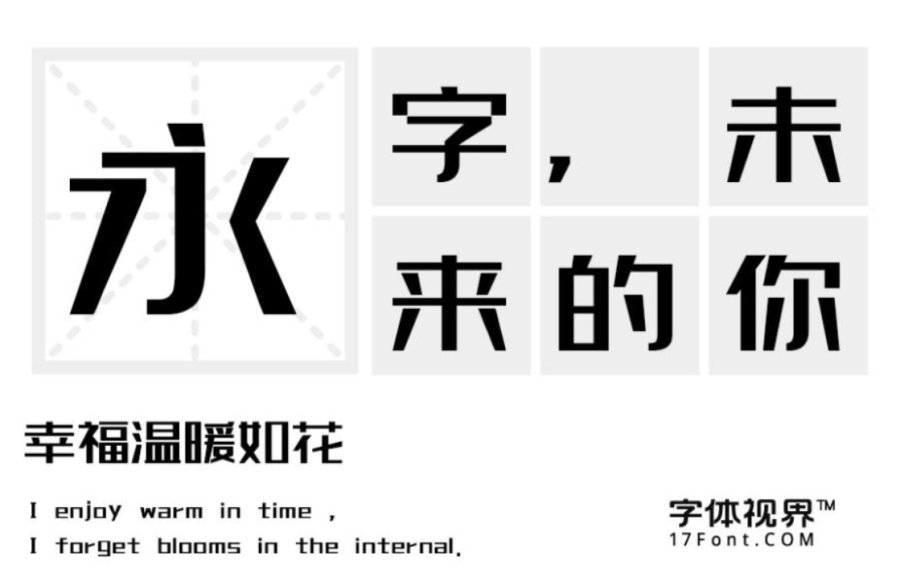
上首京东体:这款字体方中带圆,上细下粗,转折圆滑。整体特征圆柔、轻巧,时尚,适用于搭配标志、广告标语、商业广告等高端属性。
丰腴简体:这是一款是一款用短粗笔画特征构成的创意字体,字形丰腴滋润,胖瘦得体,匀称适中。个性天真可爱,富有童趣。适用于杂志、包装和品牌广告宣传设计及标题排版、招牌设计等。
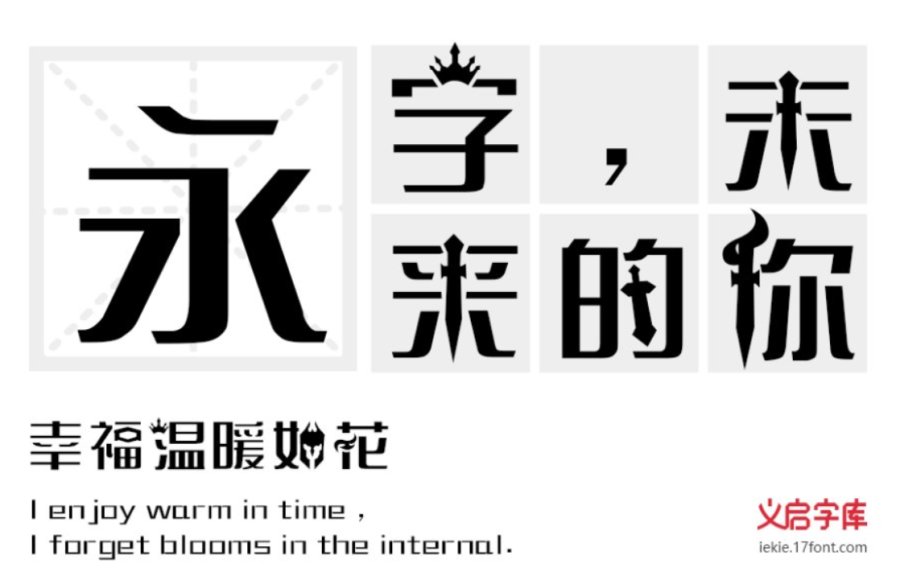
亡者农药体:这是一款极具创意的花体字,巧妙的运用了游戏的元素特征。字形粗中有细,线条流畅自然,是一款极为独特的字体,不过比起放在正文,更适合包装、logo、游戏、综艺、广告等艺术领域。